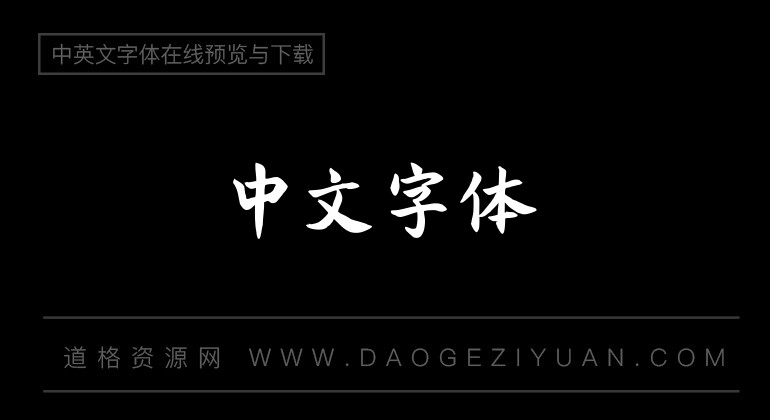
Aa语文老师的字
Aa语文老师的字字体是一种新颖、简洁、大气的字体,它以简洁的线条与笔画,以及精致的细节,表现出清新、舒缓的感觉。字体的笔画精致,曲线优美,给人以清新、优雅、大气的感觉,这是Aa语文老师喜欢的字体特点。
Aa语文老师的字是一款非常不错的手写艺术字体,具有很好的视觉感,适合于文化类的宣传设计、商业类品牌的广告和产品包装设计以及个性化文字排版等较多场景。